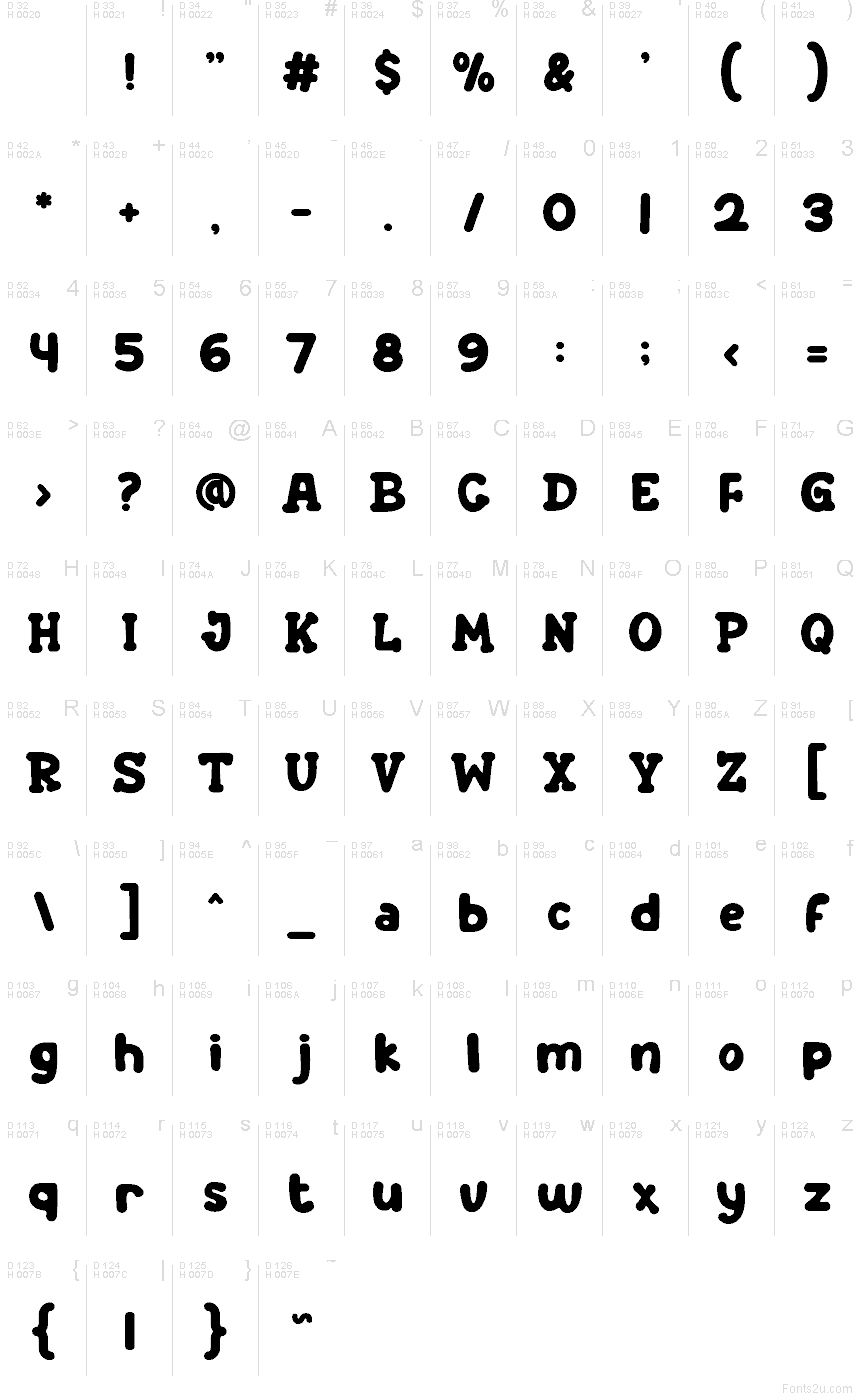
Crayon Craft
Crayon Craft od Putracetol Studio je bezplatné kreslené písmo typu display, definované svojimi vypuklými, zaoblenými tvarmi, ktoré pôsobia, ako keby boli otlačené do mäkkej hmoty. Táto nadýchaná silueta dodáva abecede priateľský a mierne neohrabaný vzhľad; nepravidelné krivky a klesajúce ťahy zabezpečujú, že dizajn pôsobí skôr ručne vytvoreným než strojeným dojmom.
Najviac sa hodí na obálky detských kníh, školské plagáty, narodeninové pozvánky, obaly na snacky a hravé náhľady na YouTube. Vďaka svojmu pružnému, vypolstrovanému objemu dokáže Crayon Craft ukotviť krátke logá alebo nadpisy v štýle nálepiek, ktoré potrebujú kreslený výraz bez zbytočného vizuálneho hluku.